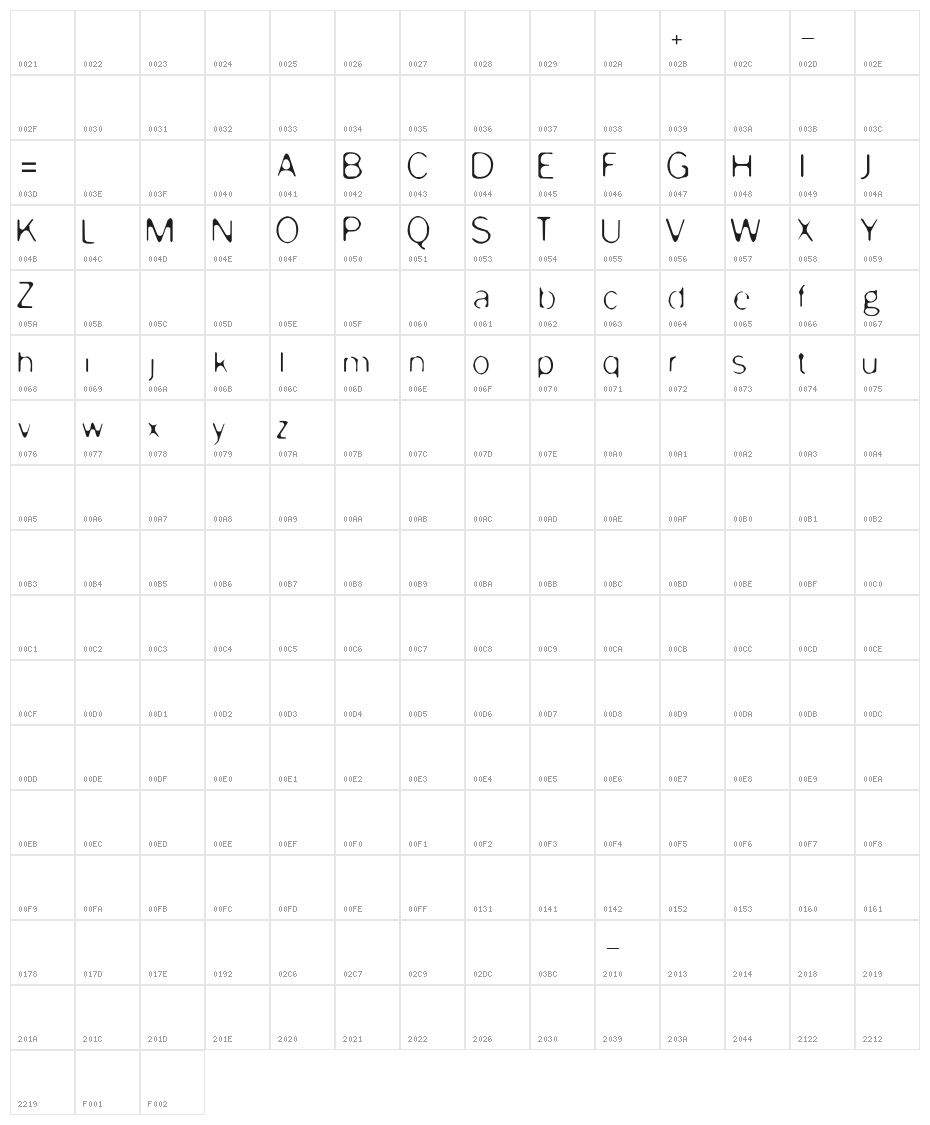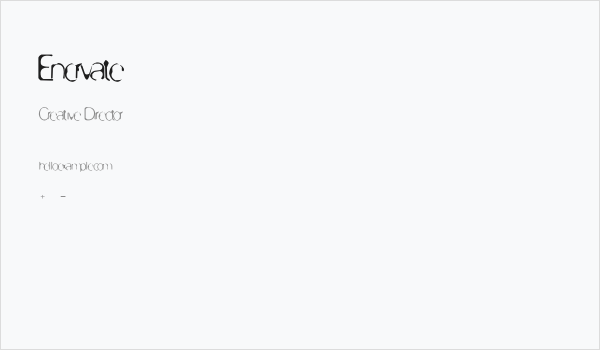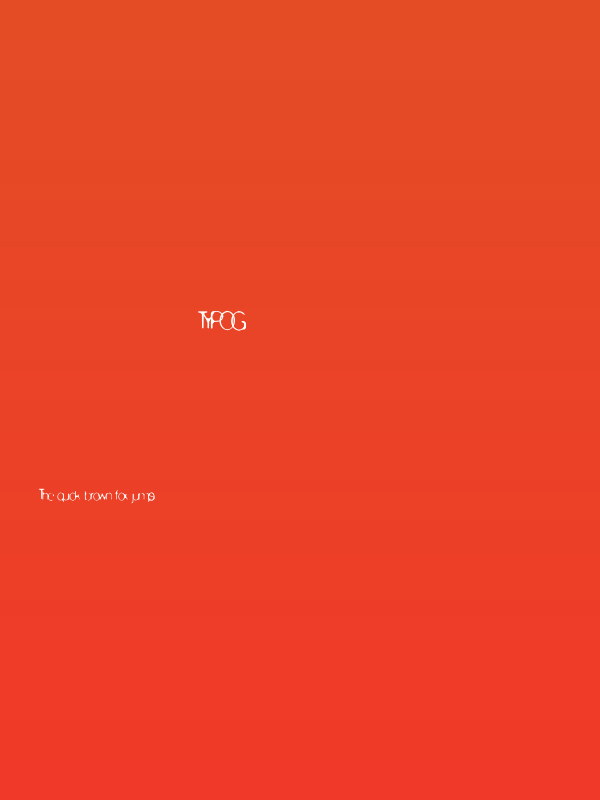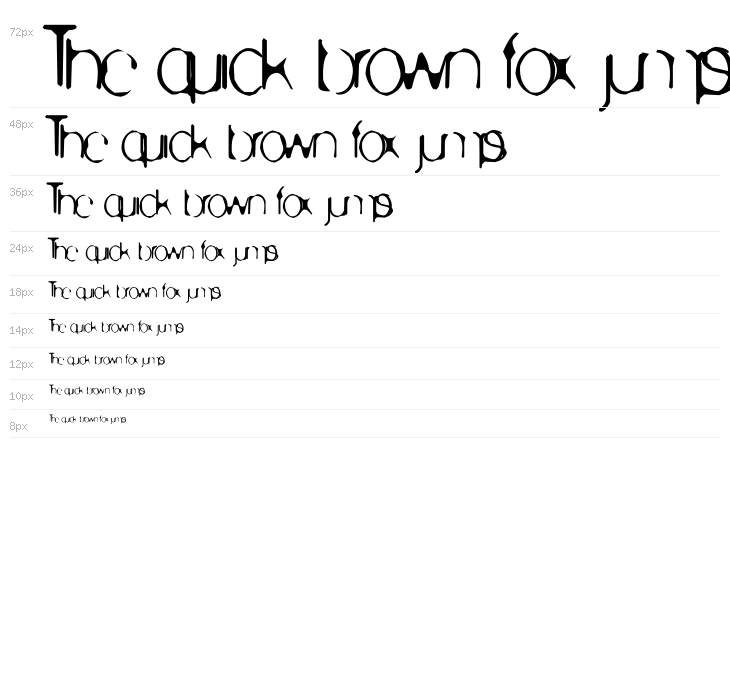
Enervate Font
✎ Distorted Eroded
| Categorie | Distorted Eroded |
| Caso d'uso | Logos, Posters, Artistic projects |
| Progetti proposti | Ideal for creative projects such as album covers, posters, and branding for avant-garde or artistic ventures. |